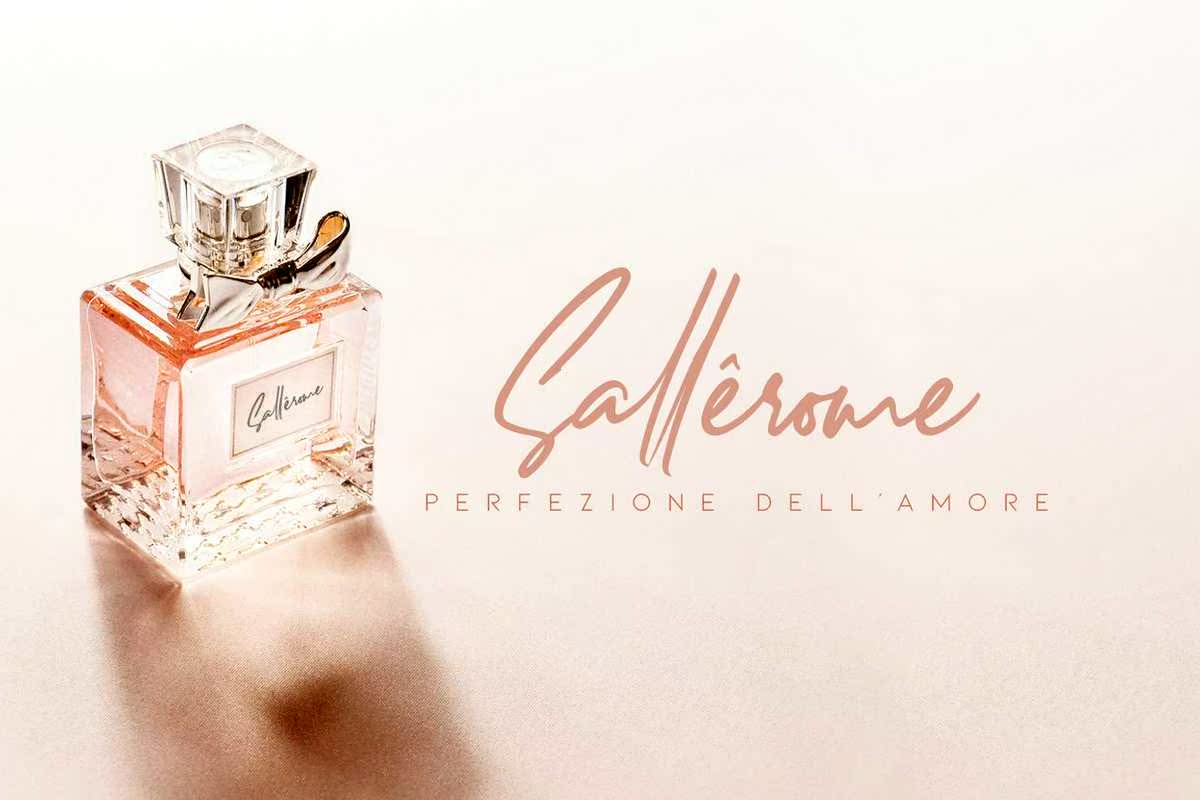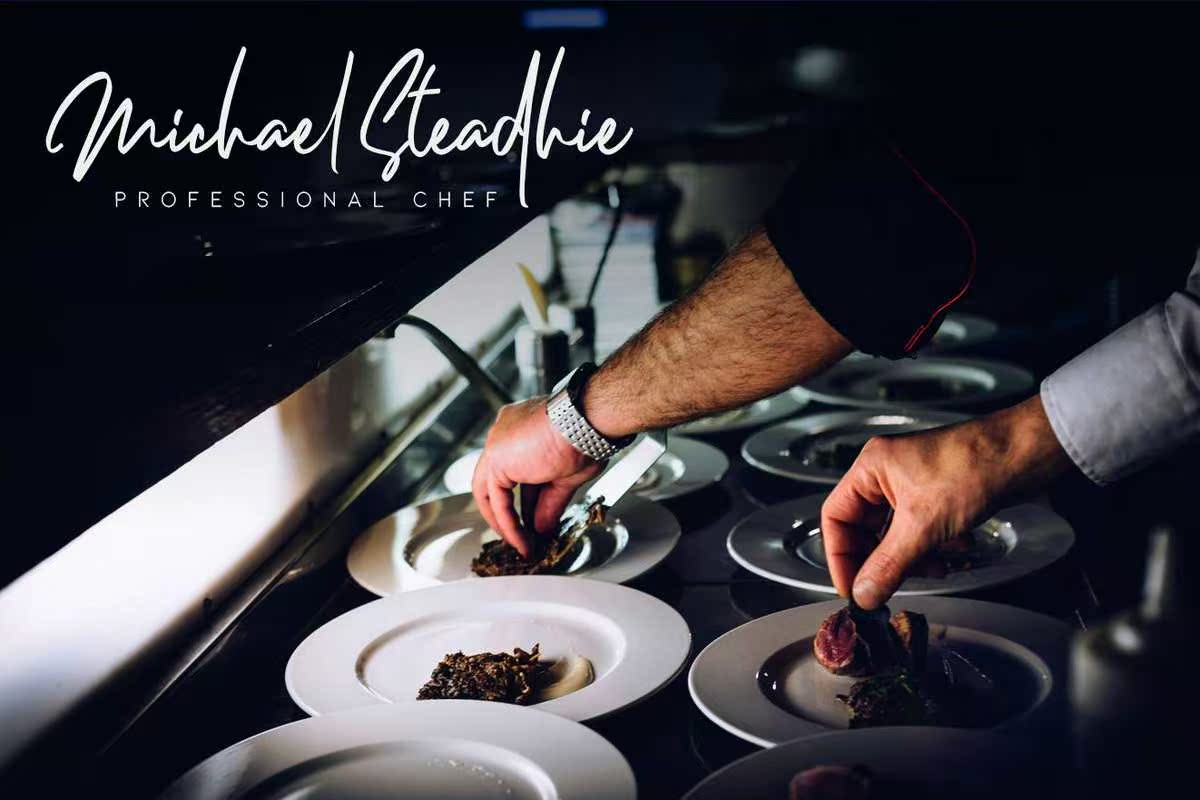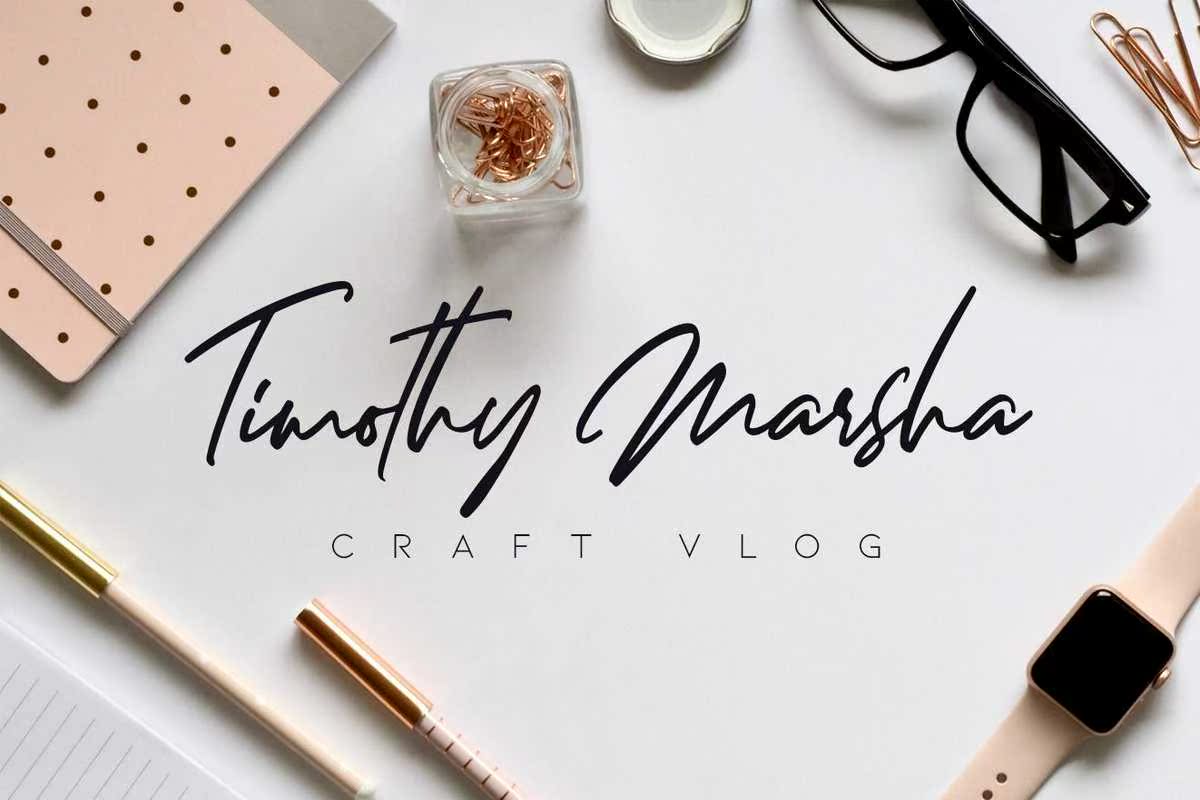
使用2种常规和艺术风格介绍DellamondeisaluxurySignatureFont。受uxury和品牌材料的启发,该Font的外观与您最近的项目几乎一致。Dellamonde适用于徽标和品牌、摄影、邀请、水印、广告、产品设计、文具、婚礼设计、标签、产品包装、,特别推荐或任何需要手工制作味道的产品。介绍2种风格的EllamondeisaluxurySignatureFont,并带有2种风格的规则和魔力。受uxurs和品牌材料的启发,这款Font看起来与您最近的项目非常相似。Dellamonde在徽标和品牌、摄影、邀请、水印、广告、产品设计、文具、婚礼设计、标签、,产品包装、特殊物品或任何需要手工书写的物品。